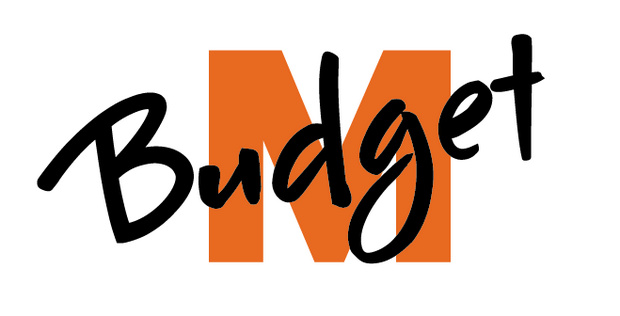
Suche Handschrift aus dem M-Budget-Logo der Migros
weiß jemand, ob Migros eine vorhandene Schrift für das "Budget" aus dem M-Budget-Logo verwendet hat oder ob nur die 6 Buchstaben speziell für den Schriftzug erstellt wurden?
Und falls letzteres der Fall ist, kennt jemand eine ähnliche Schrift?
Das sind mindestens zwei Schriften, da das B nicht zum Rest passt – allein schon aufgrund fehlender Strichstärkenunterschiede. Für den Rest könnte die McBooHmk Pate gestanden haben.